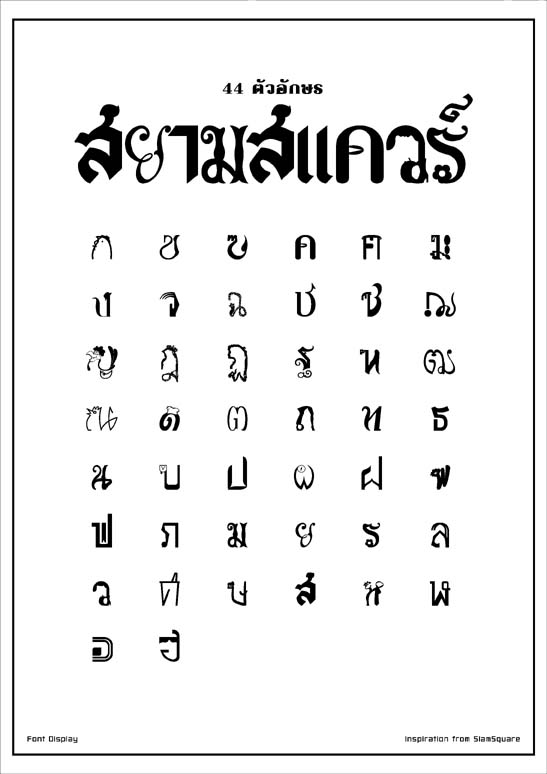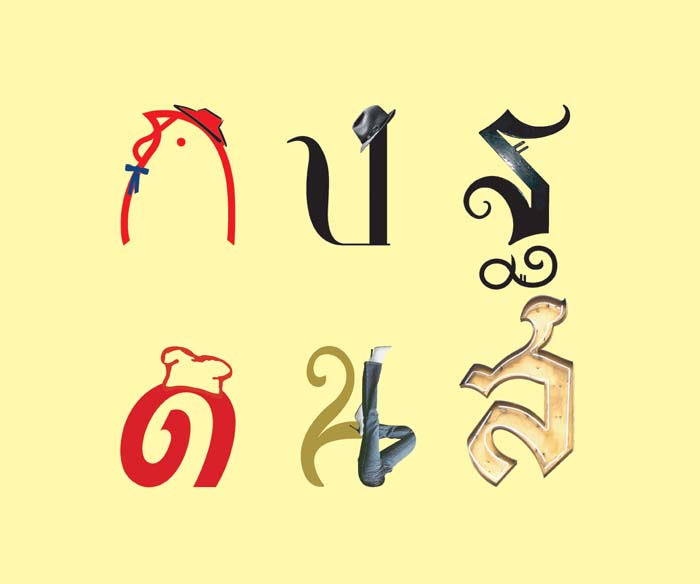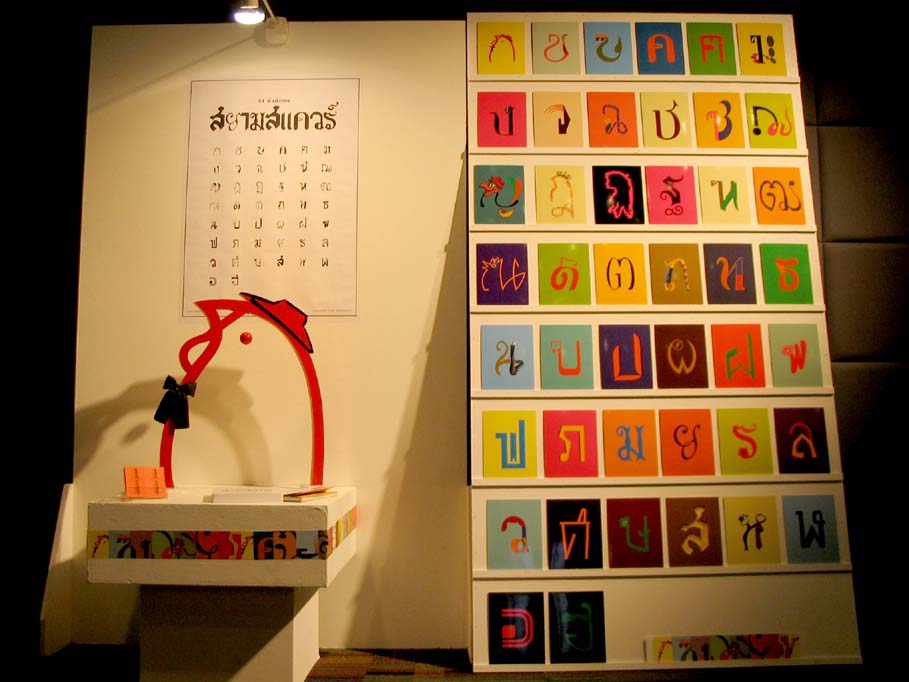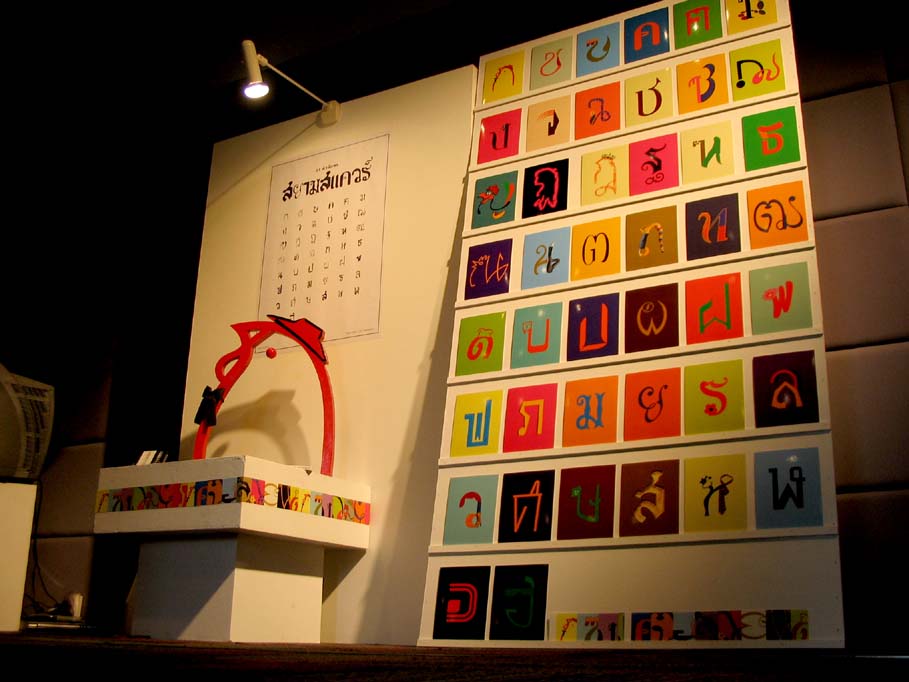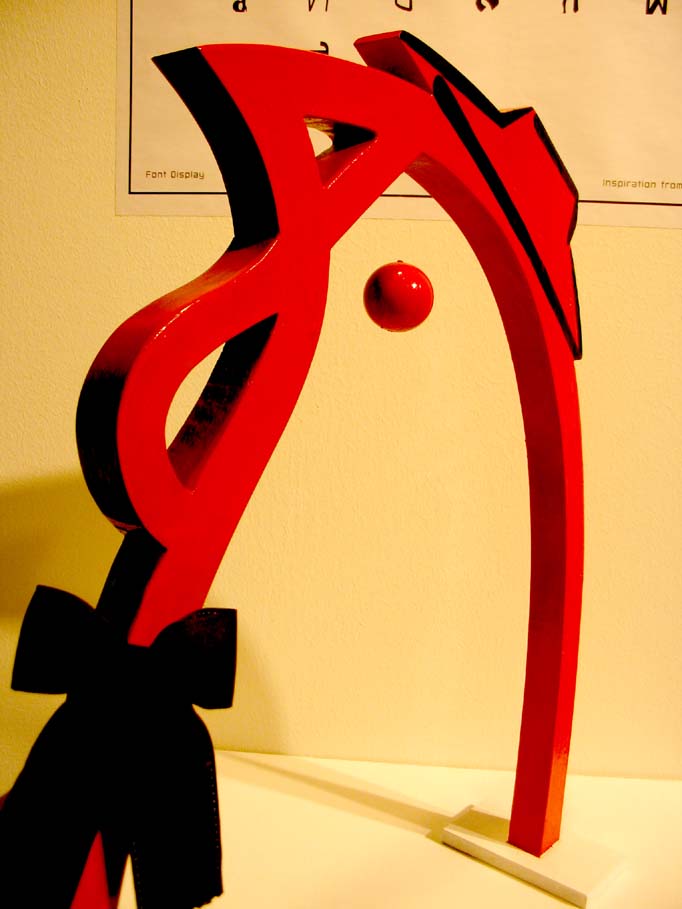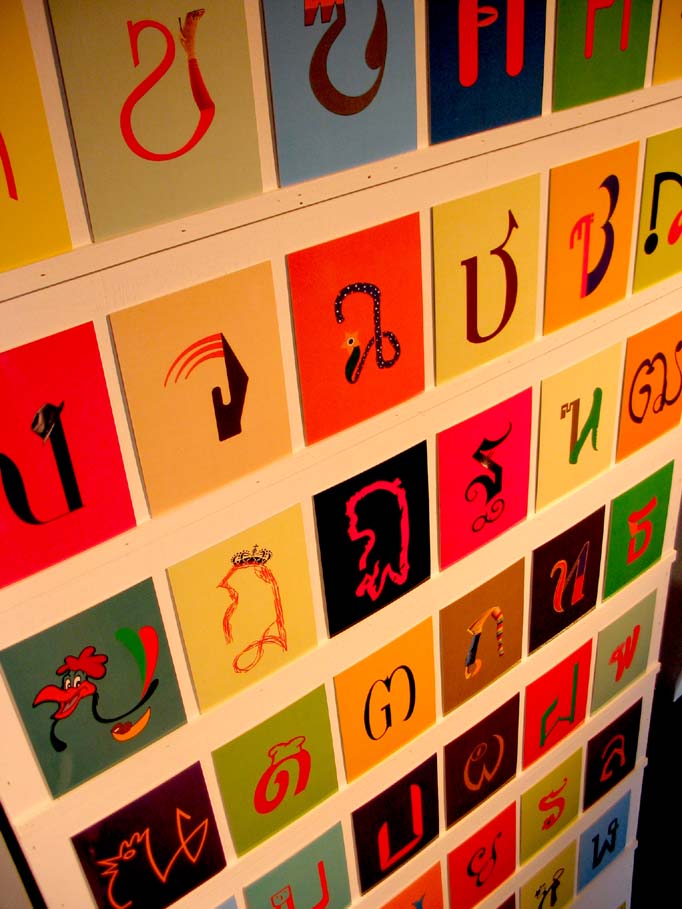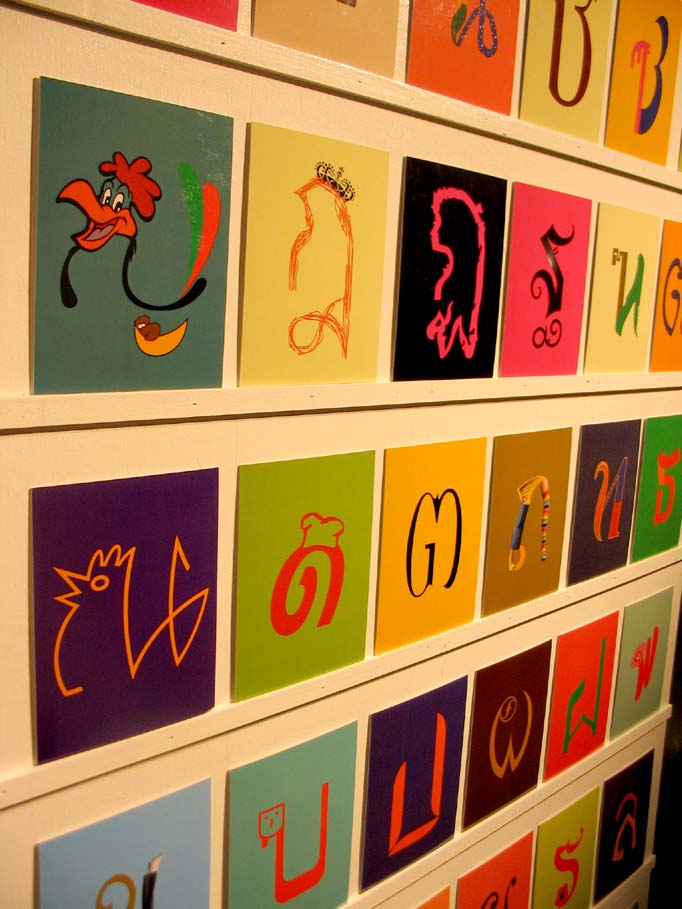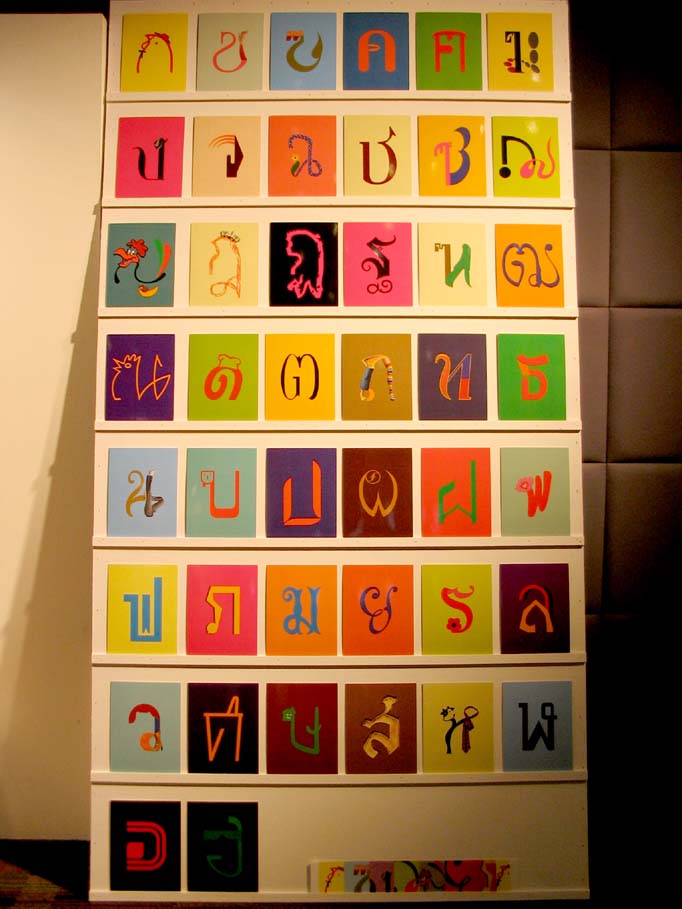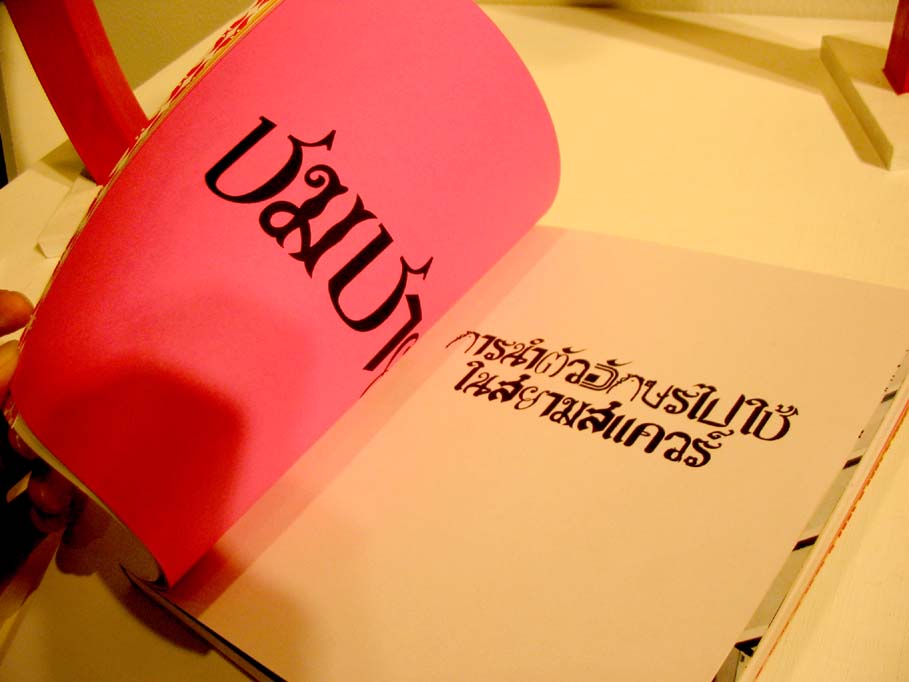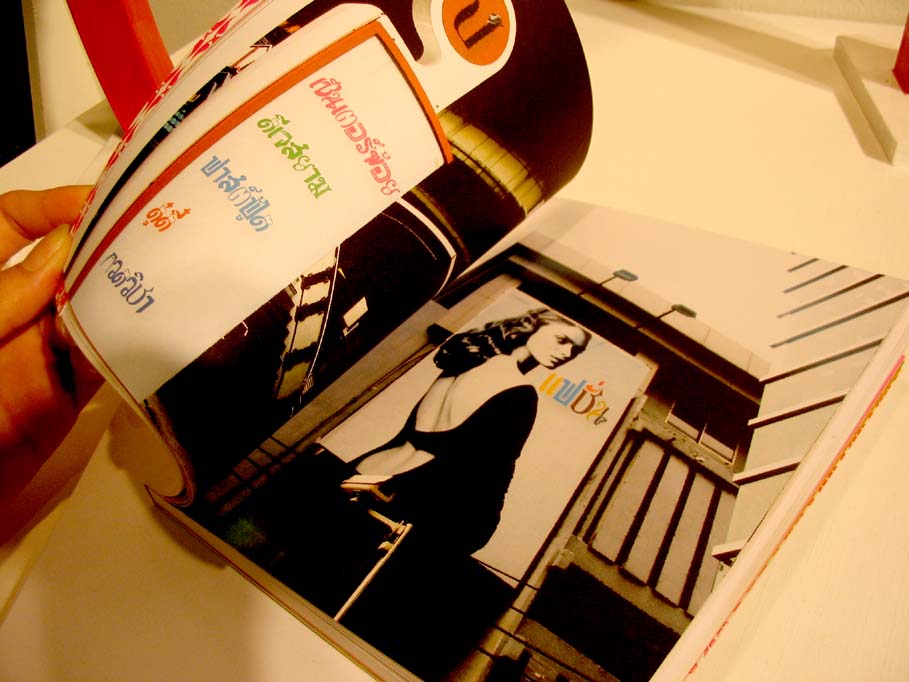
ฟ้อนสยามสแควร์
Concept  :  Inspiration from SiamSquare
ออกแบบโดย : นครินทร์ ฉัตรจรัสแสง ( โกกิ )
Concept  :  Inspiration from SiamSquare
ออกแบบโดย : นครินทร์ ฉัตรจรัสแสง ( โกกิ )
อาจนำมาเป็น pattern ของเสื้อผ้า หรือ wallpaper ได้ ซึ่งลายพวกนี้ล้วนมาจากฟ้อนของสยามสแควร์
สวยดีครับ น่าสนใจ เอาใจช่วยนะครับ สู้ต่อไป ดูแล้วดูเป็ยสยามสแควร์ชัดเจนขึ้นครับ น่าสนใจดี
// ขยายความ : สวยจริงๆ = ฟอนต์
เท่ห์ดี รู้จักเอาสัญลักษณ์มาประยุกต์ใช้ สยามน่าจะเอาไปใช้จิงๆ ....... :45: